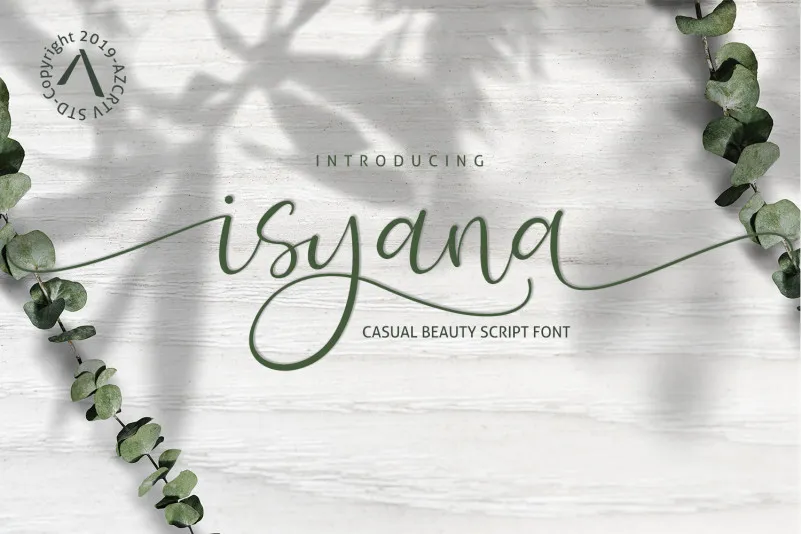
Isyana Font – Fonte Grátis
Isyana Font
Esta é uma fonte de escritura cíntica com um estilo leve e autêntico, perfeitamente adaptada para textos ornamentais ou decorativos. Isyana Font transmite uma sensação relaxante e elegante ao seu design, sendo ideal para aplicar em materiais de impressão para criação de gráficos, logotipos, mensagens personalizadas ou letras de músicas. Com um estilo clássico que parece ter saído do século XVIII, Isyana é a escolha perfeita para quem procura uma fonte elegante e única que se encaixa perfeitamente em qualquer projeto gráfico. Azcreativestd, o designer desta fonte, trouxe esta arte à vida com um toque personalizado e autêntico. O resultado final é uma combinação única de modernidade e antigo, perfeita para quem procura algo além do básico na tipografia. Para designers e profissionais da área que buscam uma fonte clássica e versátil, Isyana Font pode transformar seus trabalhos em um verdadeiro show de palmas.
Designer: azcreativestd